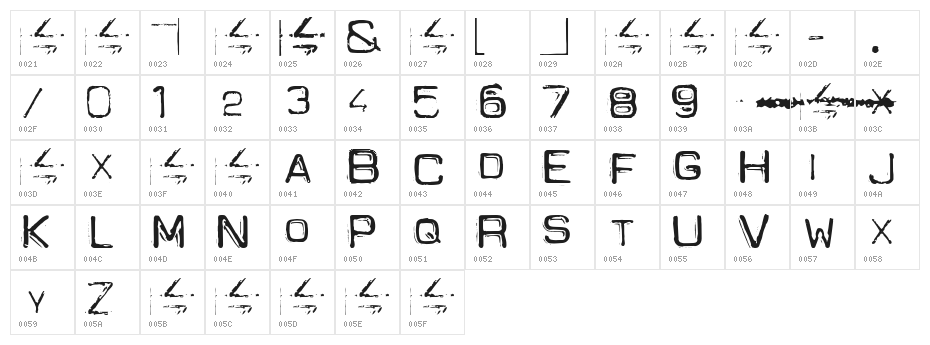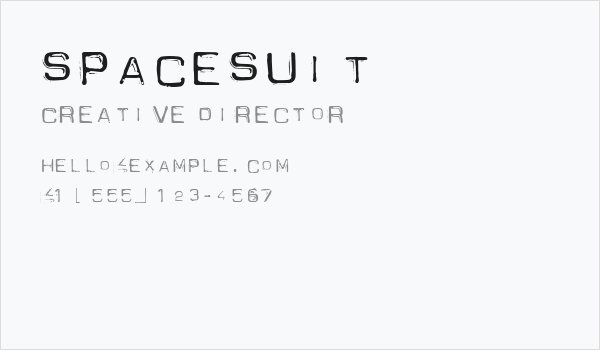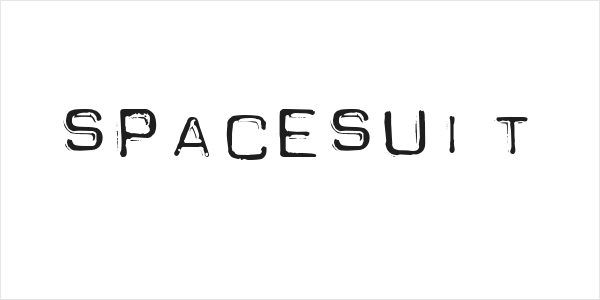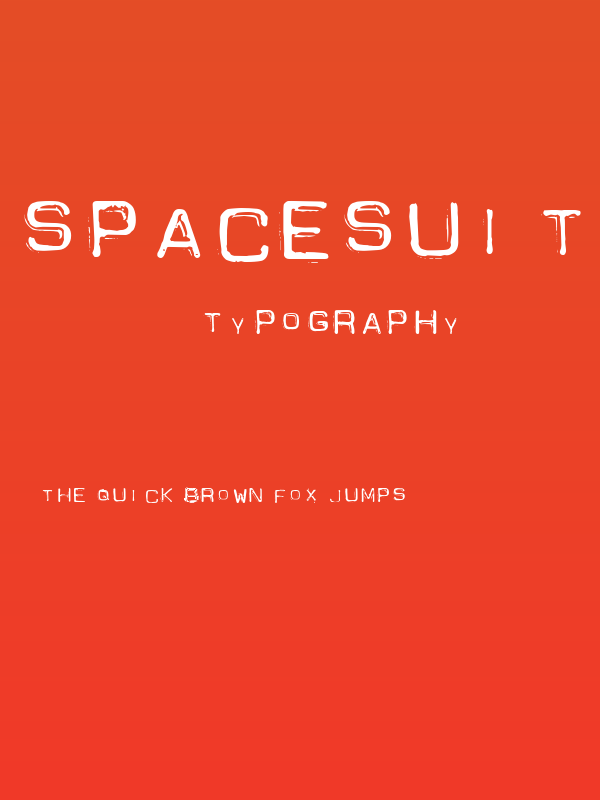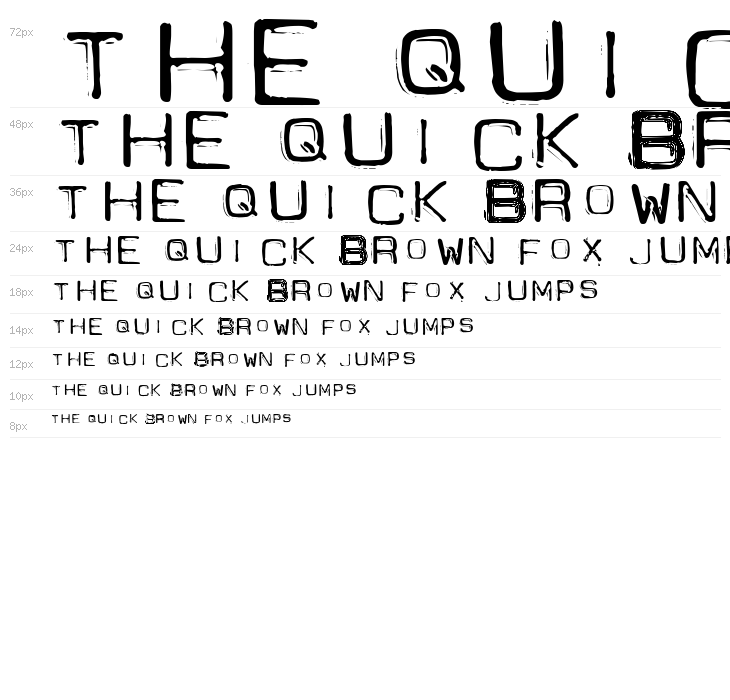
Spacesuit Font
| Stile generale | Vintage, Industrial, Grunge |
| Progetti proposti | This font is perfect for projects such as album covers, posters, branding for industrial or vintage-themed businesses, and any design that requires a bold, gritty look. |